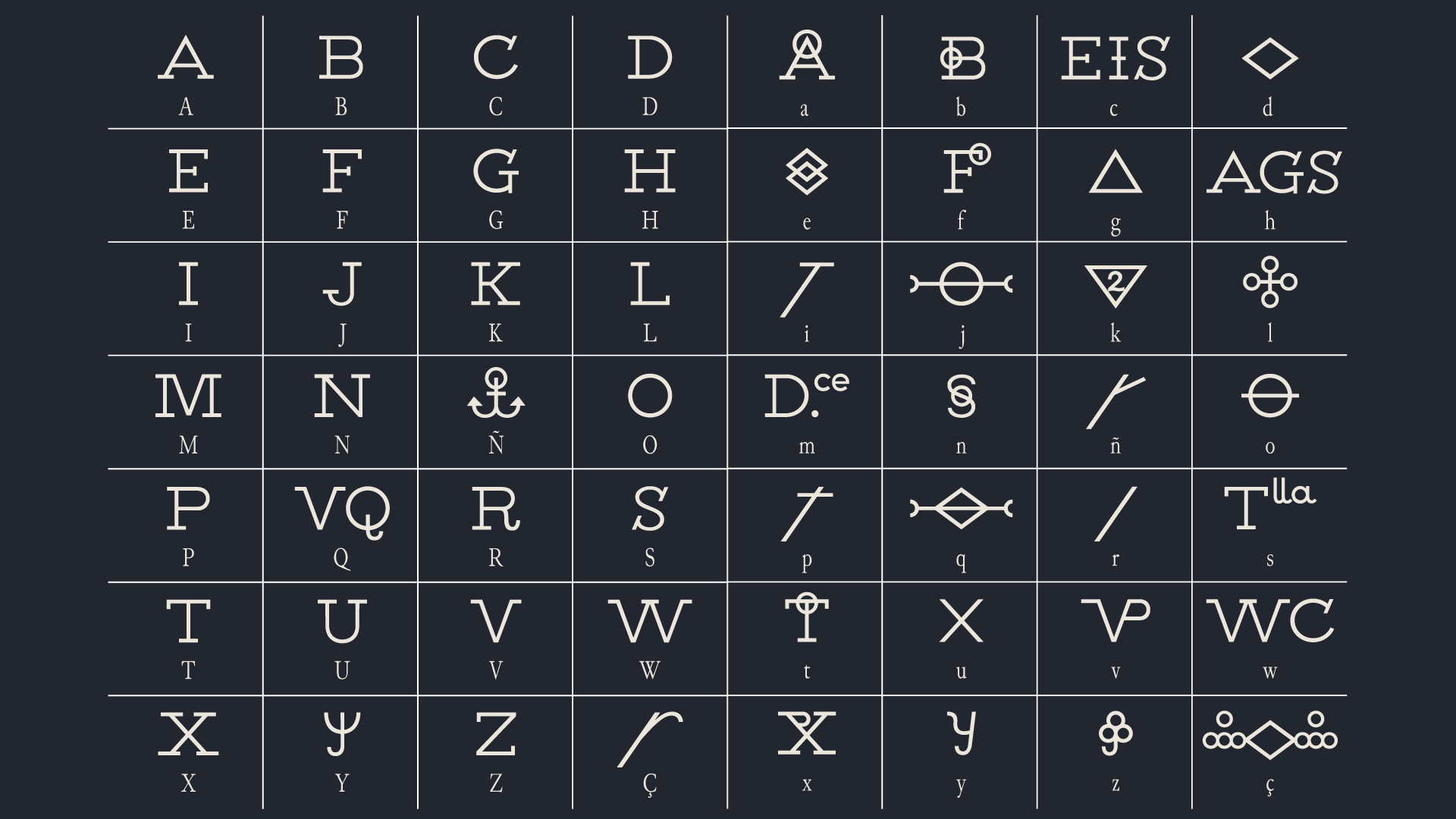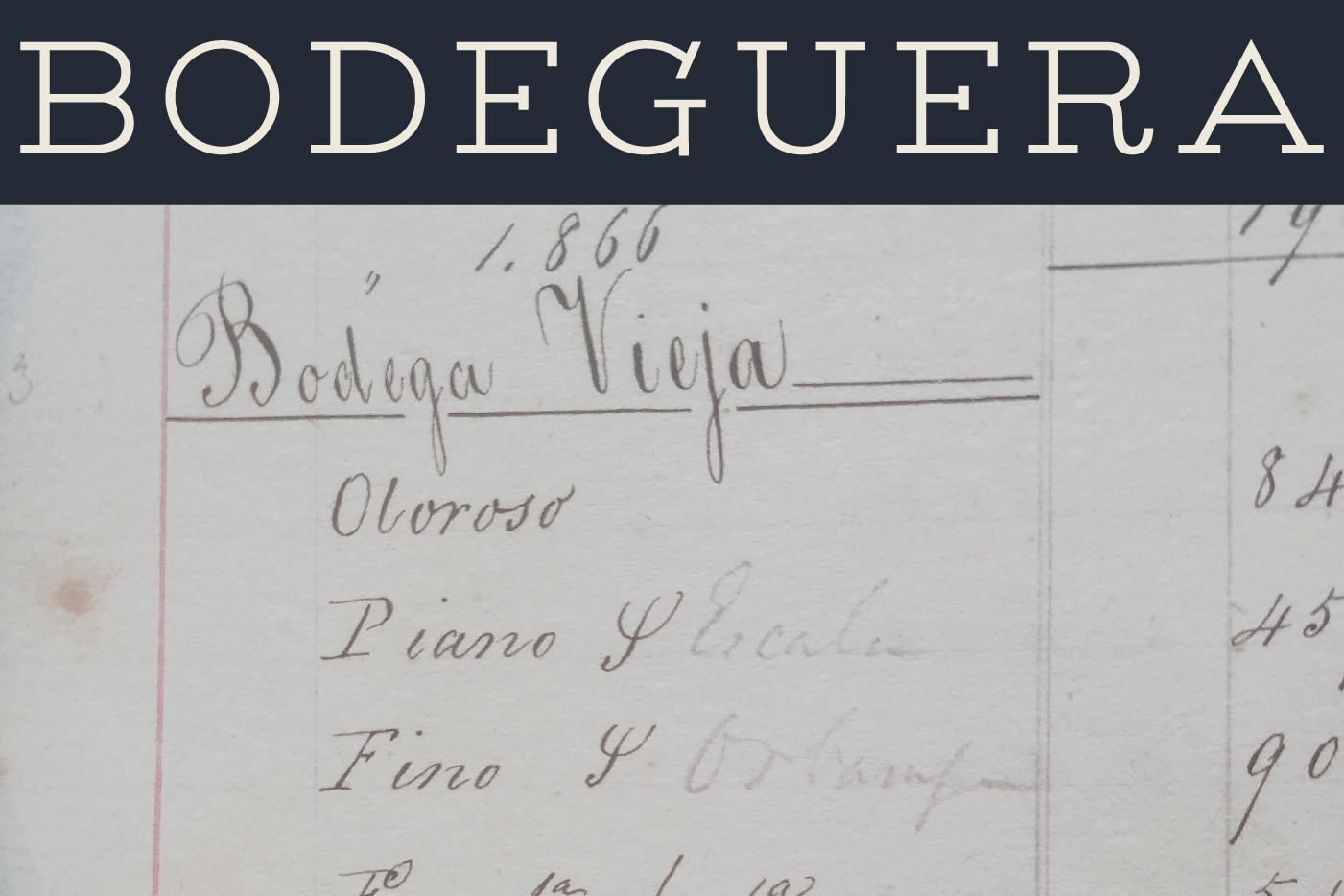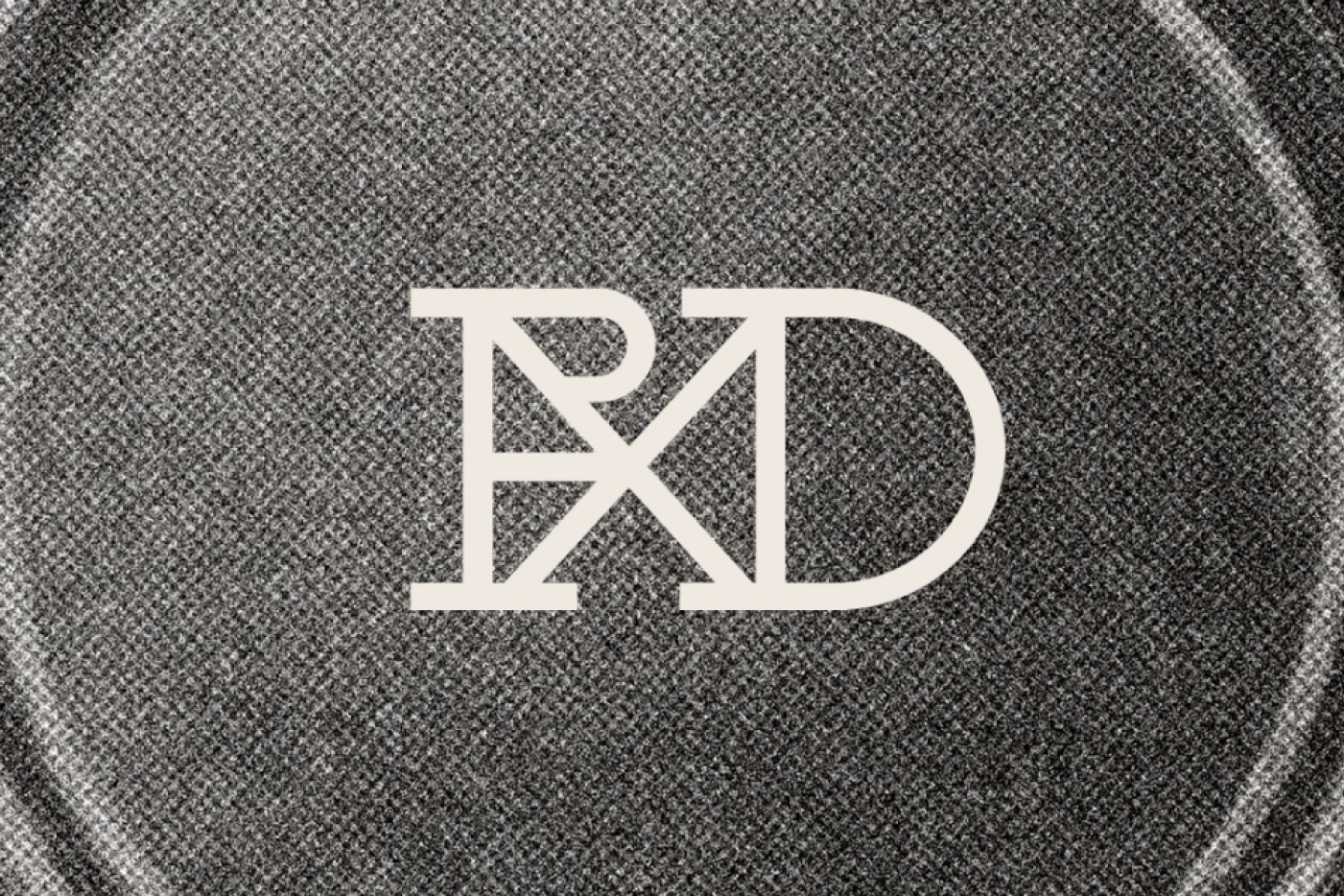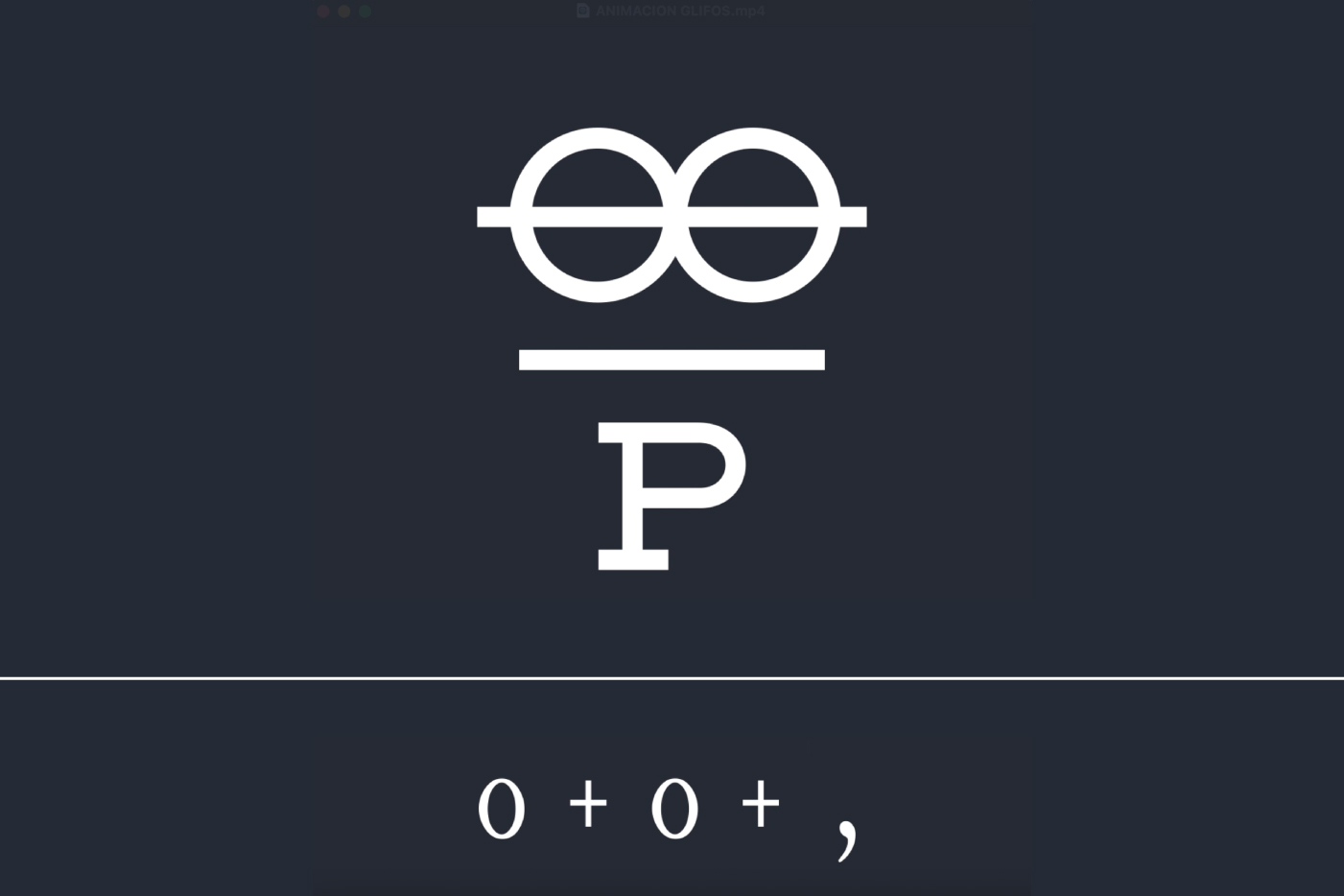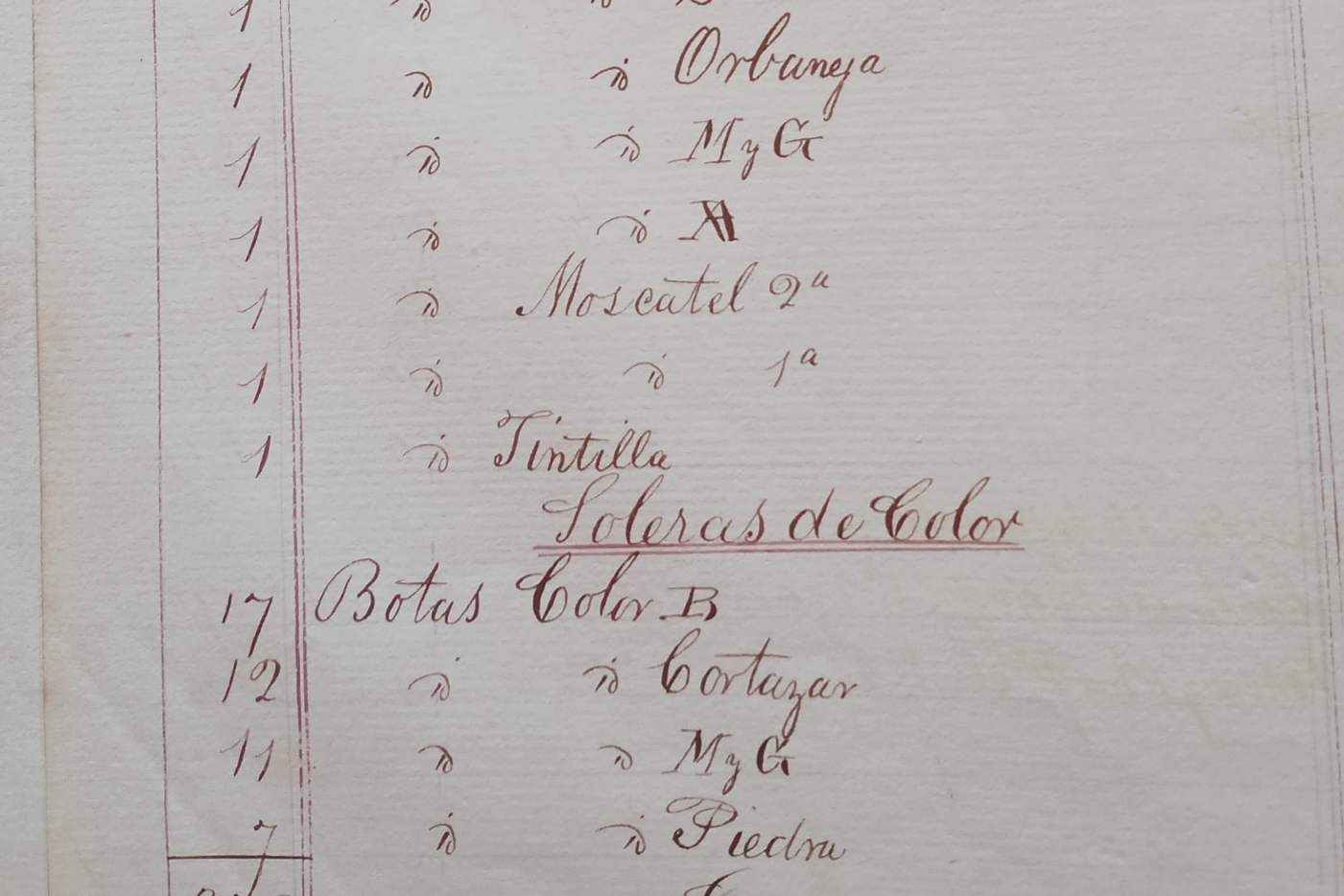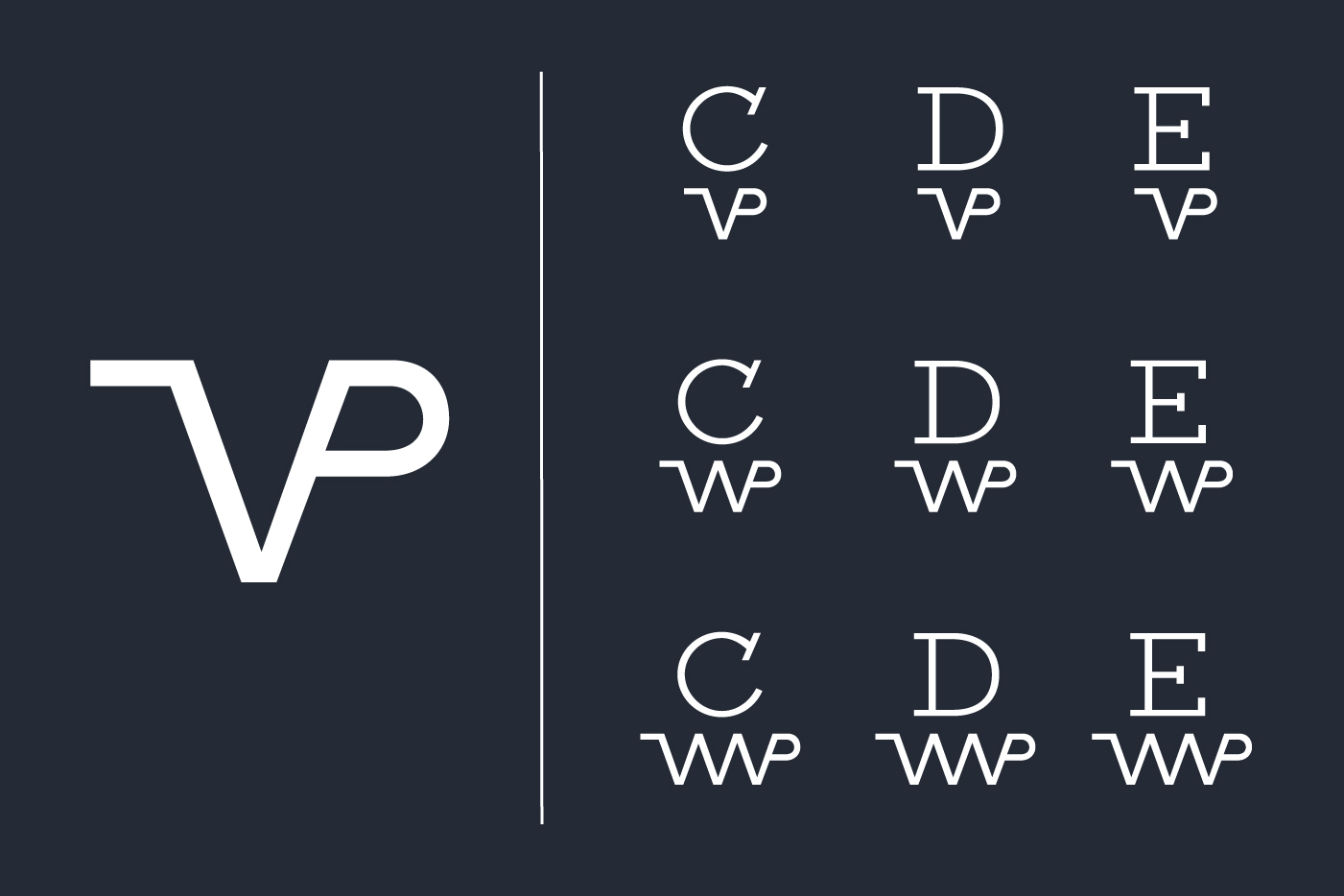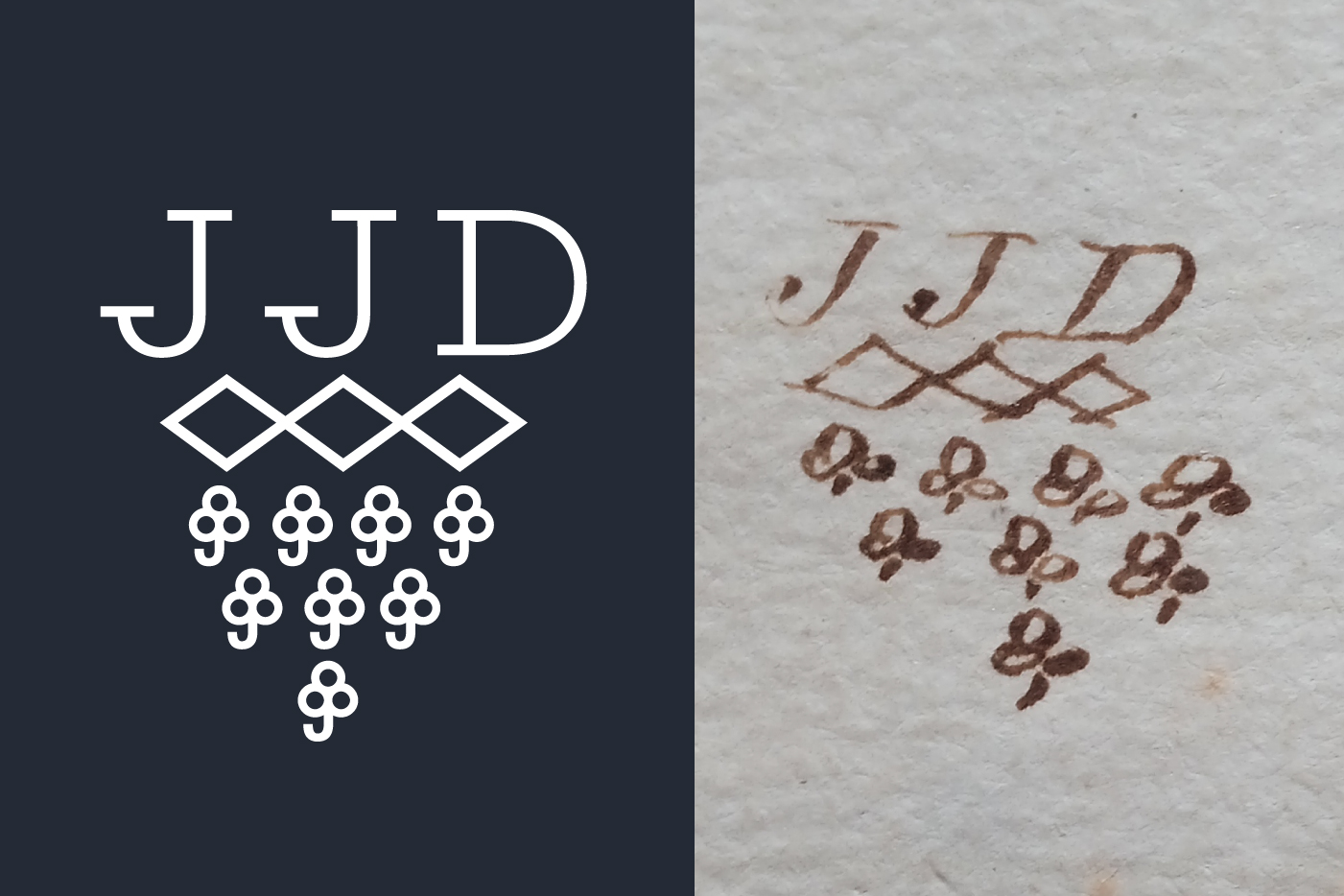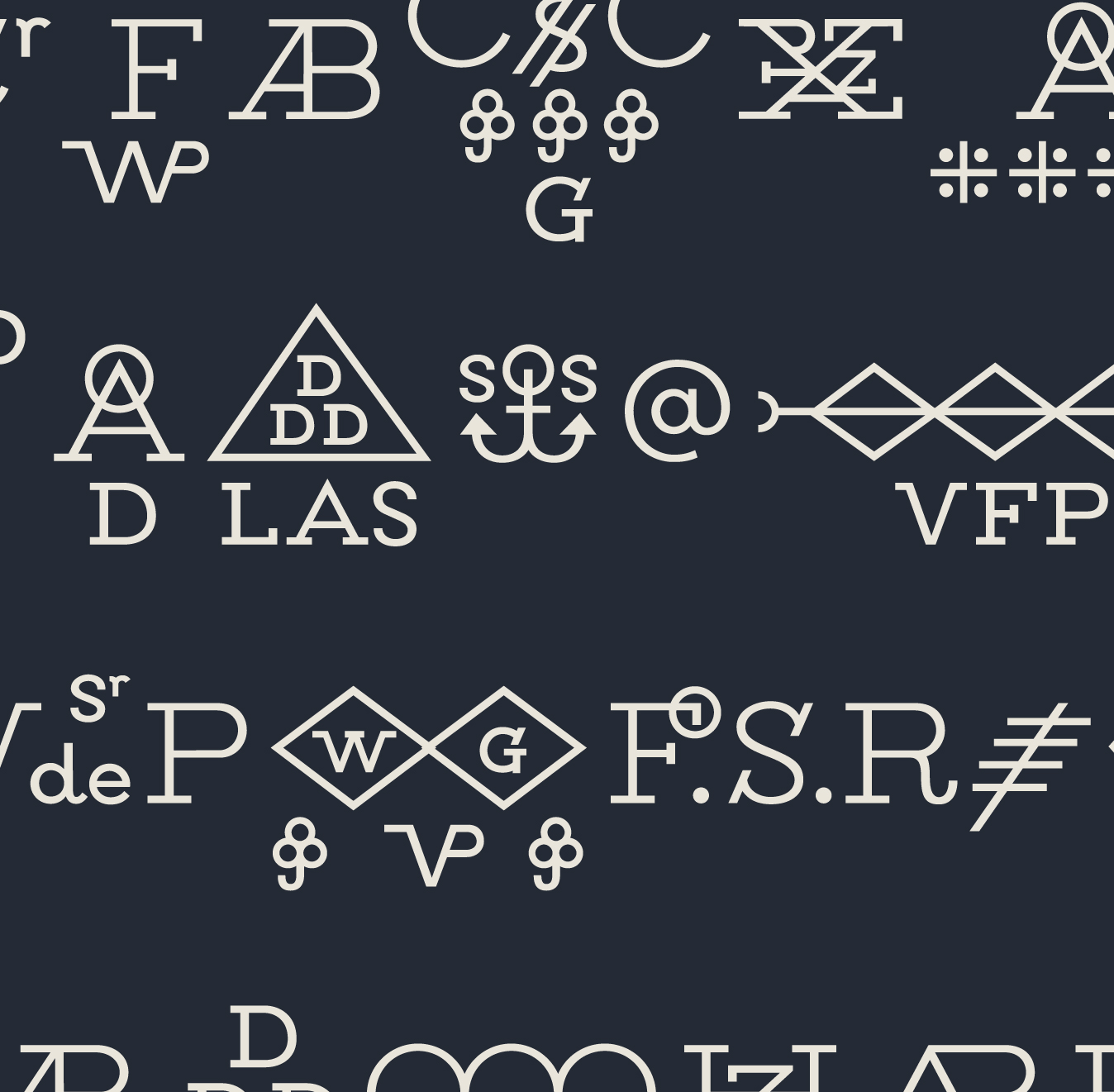
BODEGUERA
Los símbolos del vino
BODEGUERA
Los símbolos del vino
Patrimonio e historia de la bodega
Bodeguera. Los símbolos del vino de Jerez
Bodeguera es una tipografía de alma gestual y oficio, nacida de la tiza y de la exportación mundial del vino. Su diseño se fundamenta en el estudio de los primeros libros de contabilidad y de embarque fechados entre 1838 y 1860, de la bodega González Byass. Rescata todo el sistema de marcas que hacían los trabajadores de las bodegas en los toneles para controlar todos sus tipos de vinos.
En Despacho de Tipos, no solo fundimos letras; custodiamos el rico pasado industrial bodeguero y sus oficios a través de la gráfica. Bodeguera actúa como un puente genealógico diseñado para potenciar la herencia del Marco de Jerez, respondiendo a las necesidades de identidad vitivinícola.
Identidad de marca y herencia bodeguera
Estamos hablando que por esas fechas el vino de Jerez se exportaba con unas características, totalmente personalizadas, y a medida del gusto del consumidor. Más de 800 tipos de vinos, características y marcas a fuego, todos relacionados a partir de un sistema unificado, simple y con identidad.
El lenguaje del vino
La versatilidad de Bodeguera se despliega en una versión digital fiel al archivo bodeguero, con una intención de identidad de marca, y en forma de nuevo lenguaje gráfico. Recupera los símbolos del vino de las botas del XIX, y los integra en un nuevo diseño de alfabeto, con un sistema de combinaciones de signos normalizados, donde cada combinación tiene sentido.
Bodeguera. Los símbolos del vino de Jerez
Bodeguera es una tipografía de alma gestual y oficio, nacida de la tiza y de la exportación mundial del vino. Su diseño se fundamenta en el estudio de los primeros libros de contabilidad y de embarque fechados entre 1838 y 1860, de la bodega González Byass. Rescata todo el sistema de marcas que hacían los trabajadores de las bodegas en los toneles para controlar todos sus tipos de vinos.
En Despacho de Tipos, no solo fundimos letras; custodiamos el rico pasado industrial bodeguero y sus oficios a través de la gráfica. Bodeguera actúa como un puente genealógico diseñado para potenciar la herencia del Marco de Jerez, respondiendo a las necesidades de identidad vitivinícola.
Identidad de marca y herencia bodeguera
Estamos hablando que por esas fechas el vino de Jerez se exportaba con unas características, totalmente personalizadas, y a medida del gusto del consumidor. Más de 800 tipos de vinos, características y marcas a fuego, todos relacionados a partir de un sistema unificado, simple y con identidad.
El lenguaje del vino
La versatilidad de Bodeguera se despliega en una versión digital fiel al archivo bodeguero, con una intención de identidad de marca, y en forma de nuevo lenguaje gráfico. Recupera los símbolos del vino de las botas del XIX, y los integra en un nuevo diseño de alfabeto, con un sistema de combinaciones de signos normalizados, donde cada combinación tiene sentido.
| Distribución: Despacho de Tipos |
Letras base
Ligaduras simples
Ligaduras compuestas
Caracteres especiales
Bodeguera
Bodeguera. Las marcas de tiza con más solera, ahora disponible para sus mejores diseños de identidad. 813 símbolos desarrollados a partir de ligaduras y combinaciones entre ellas. Pruébelas también como elementos iconográficos, infográficos o para productos relacionados con el mundo del vino.
Bodeguera
Bodeguera. Las marcas de tiza con más solera, ahora disponible para sus mejores diseños de identidad. 813 símbolos desarrollados a partir de ligaduras y combinaciones entre ellas. Pruébelas también como elementos iconográficos, infográficos o para productos relacionados con el mundo del vino.